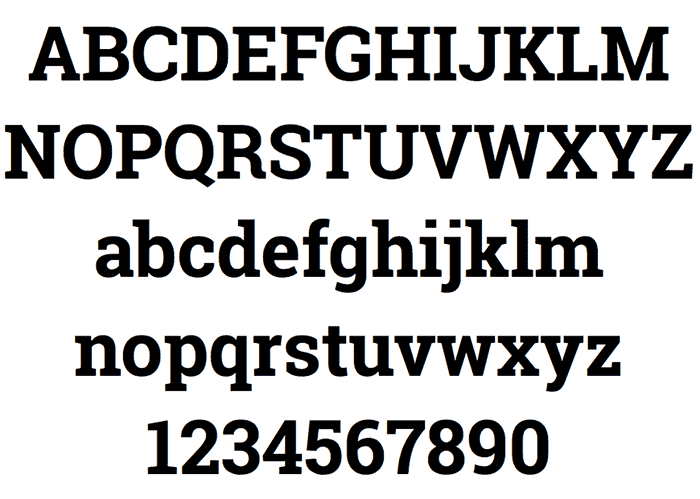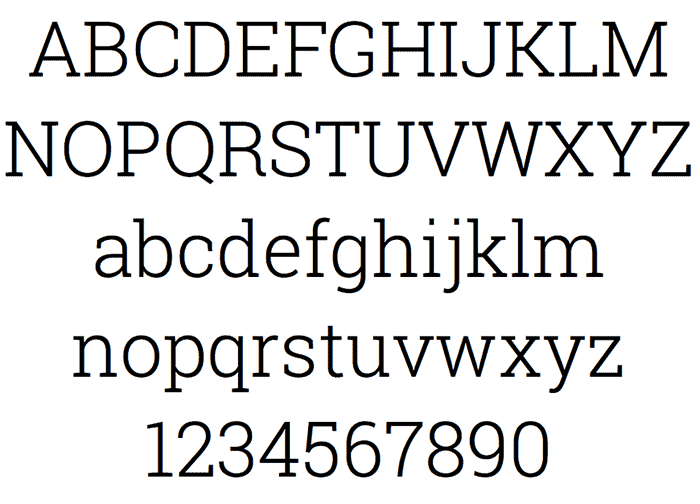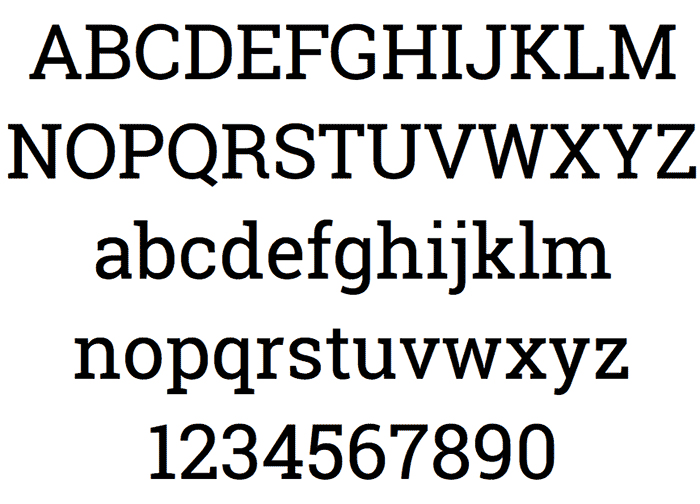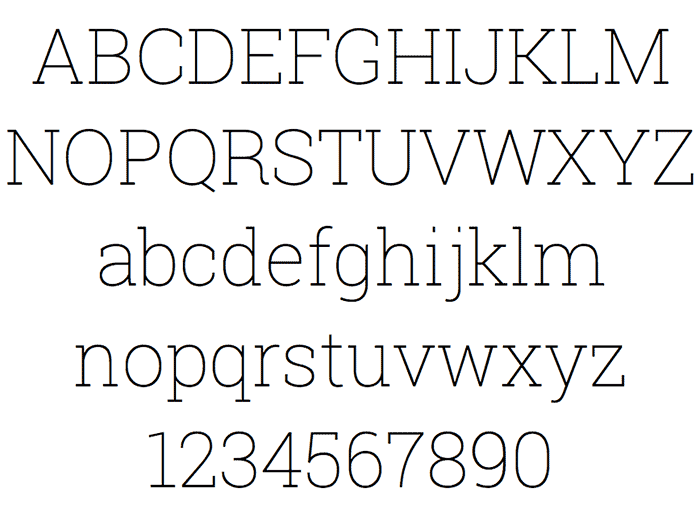
Roboto Slab ist eine serifenbetonte Version zum Android-Systemfont Roboto. Die Roboto Slab verfügt derzeit über 4 aufrechte Schnitte mit erweiterter lateinischer, griechischer und kyrillischer Belegung.